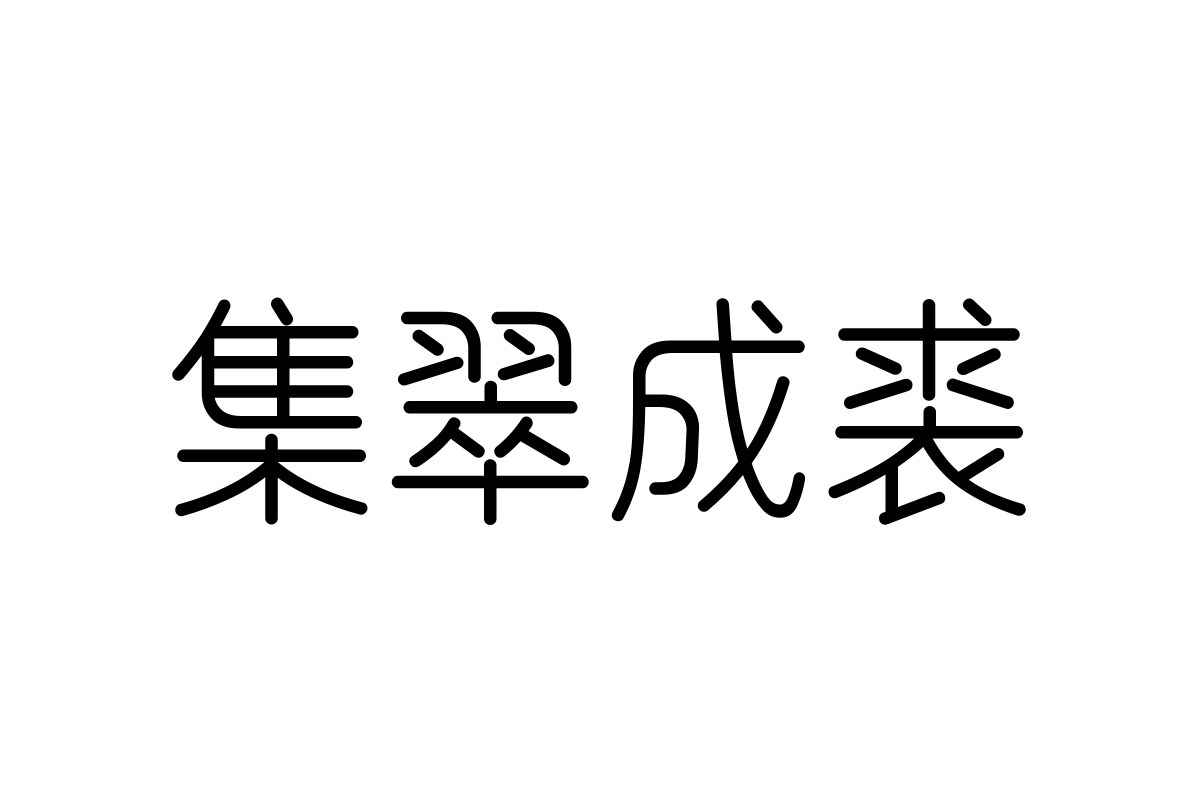
三极文圆简体字体是一种具有独特风格的中文字体,由三极文化公司设计。该字体以其圆润、流畅的线条和独特的字形结构而闻名。它的特点是笔画粗细适中,结构紧凑,给人一种简洁明快的感觉。
三极文圆简体字体适用于多种应用场景,包括标题、正文、广告等。它的设计灵感来源于中国传统书法艺术,但又融入了现代审美元素,使其既保留了传统韵味,又不失时尚感。
总的来说,三极文圆简体字体是一种具有独特魅力的中文字体,适合用于需要强调简洁、明快风格的场景。